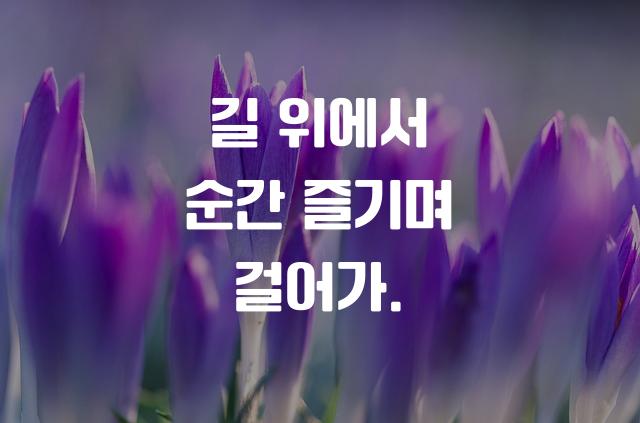
MBC1961은 (주)문화방송에서 제작한 기본 고딕 스타일의 두꺼운 폰트로, 제목용으로 적합하며 강한 인상과 함께 꽉 찬 느낌을 제공합니다. 브랜드의 강력한 메시지 전달에 최적화되어 있습니다.
MBC1961은(는)
기본 고딕, 두꺼운 스타일, 굵은 고딕, 감성적인, 단단함, 부드러움, 길고/크고 계열의 생김새를 가지고 있으며
광고 캠페인, 웹/앱 디자인, 출판물 제목 등에서 자주 활용되며, 효과적인 메시지 전달에 적합합니다.
이 폰트는 출판/미디어, 문화/예술, 엔터테인먼트 분야에 잘 어울리며,
신뢰감, 전문적인, 클래식한 느낌을 담고 있는 것이 특징입니다.